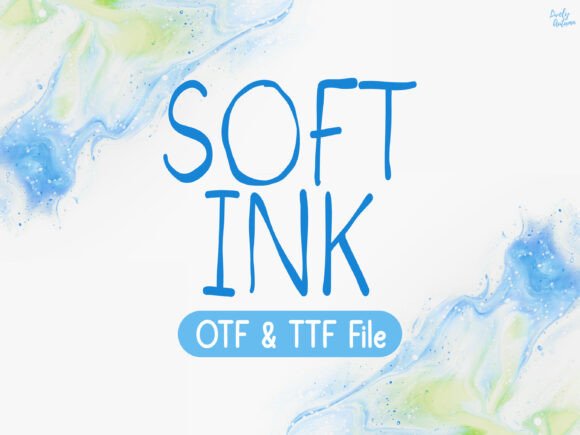
Soft Ink
Soft Ink : La police manuscrite qui fait briller vos projets
Vous cherchez une police qui combine l’authenticité d’un écrit à la main et le dynamisme d’une brosse à encre ? Soft Ink est votre nouveau meilleur allié. Conçue avec une touche de charme rustique, cette police manuscrite offre des traits fluides et un effet de dégradé qui donne à chaque lettre une personnalité unique.
Pourquoi Soft Ink fait la différence
- Style brosse d’encre distinctif : chaque caractère reflète la finesse d’un pinceau, idéal pour les titres et les éléments décoratifs.
- Polyvalence exceptionnelle : du texte d’invitation à la mise en page de votre blog, en passant par les affiches publicitaires.
Applications concrètes
Soft Ink se prête à de nombreux formats :
- Invitations de mariage et cartes de vœux : un ton chaleureux pour des moments mémorables.
- Affiches et posters : la police apporte du caractère à vos annonces visuelles.
- Graphismes réseaux sociaux : accrochez l’attention de votre audience avec un texte vivant.
- Journaux et carnets de notes : ajoutez une touche créative à vos pages personnelles.
- Logo et identités visuelles : soft mais impactant, parfait pour les marques à l’esprit artisanal.
Conclusion : Soft Ink, votre nouvel incontournable
Que vous soyez graphiste, créateur de contenu ou simplement passionné par le design, Soft Ink apporte une dimension manuscrite authentique à chaque projet. Essayez-la aujourd’hui, et transformez vos idées en œuvres d’art qui parlent d’elles-mêmes.